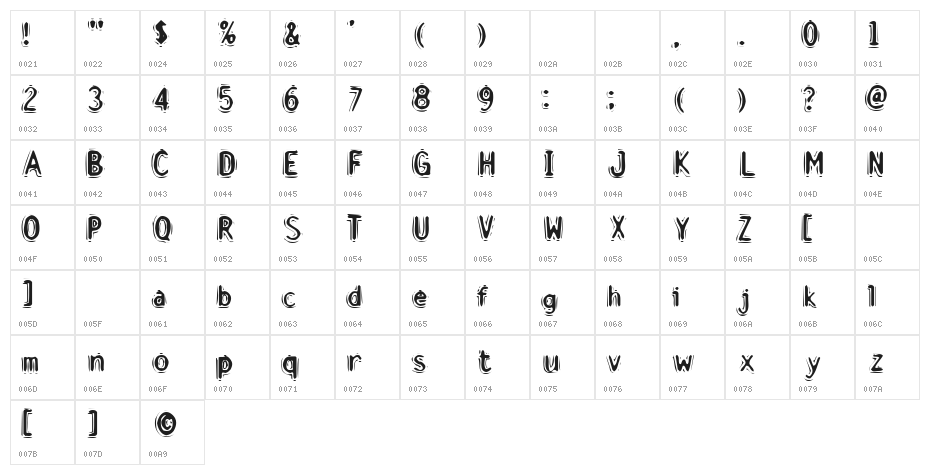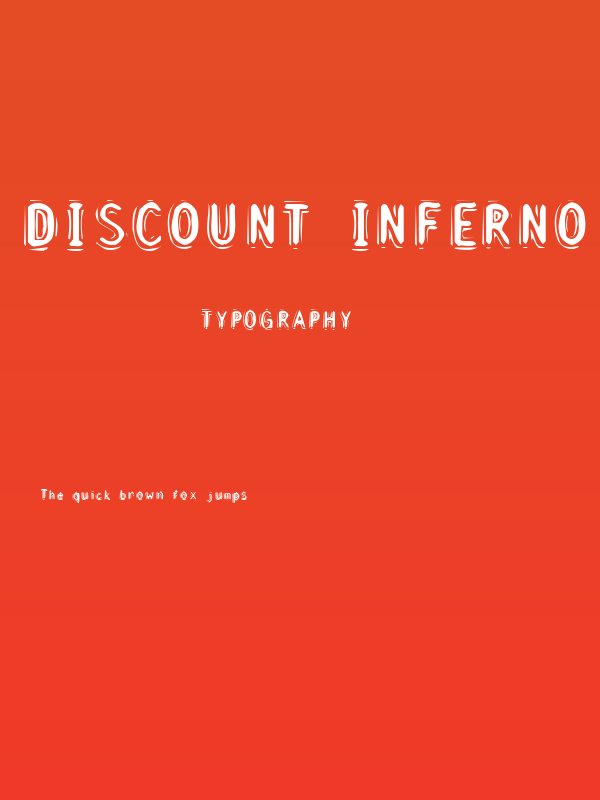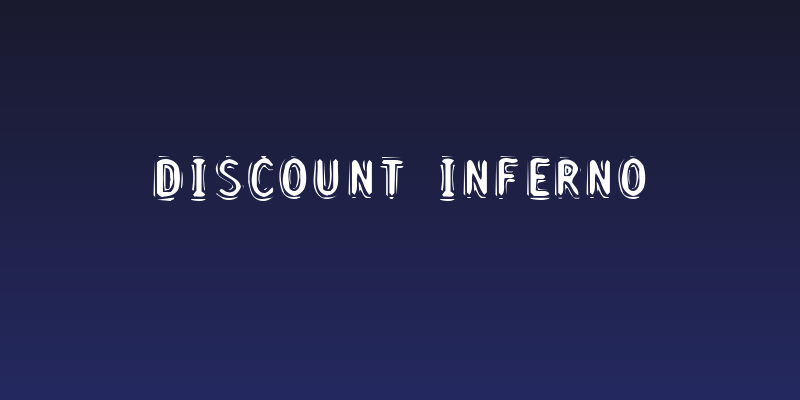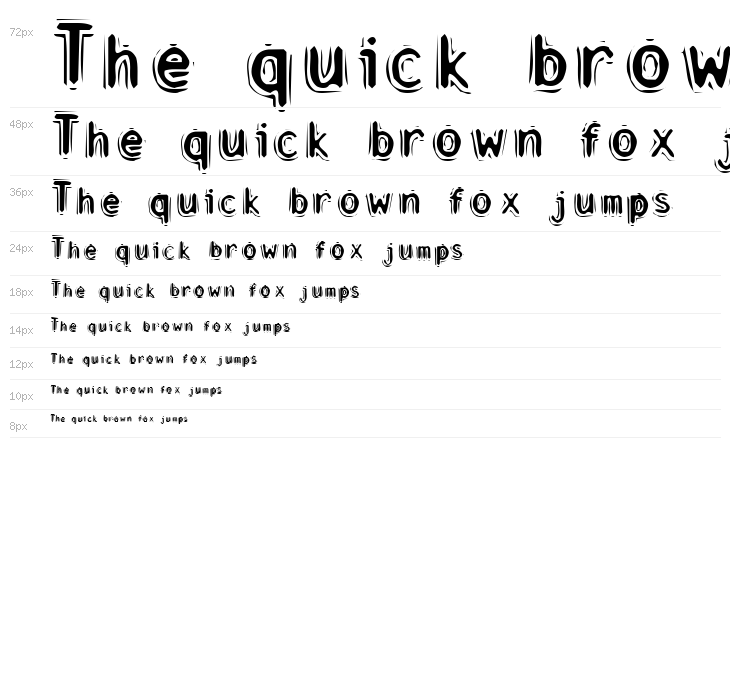
Discount Inferno Font
✎ Distorted Eroded
| Progetti proposti | Ideal for posters, event flyers, children's book covers, and branding that requires a lively and engaging typeface. |